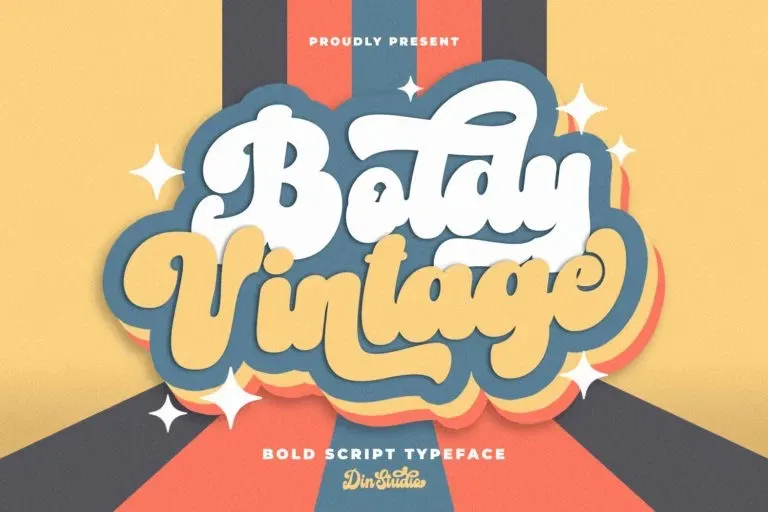
A nova fonte “Boldy Vintage Font”, categorizada como Script Fonts, é uma escolha perfeita para criar design único e inovador. Esta tipografia é marcada por um forte estilo script com um toque vintage que se destaca do restante. Foi criado pelo talentoso designer Din Studio. A fonte traz uma sensação de nostalgia moderna, onde cada traço desenhado a mão e curva exibe originalidade. Ela adicionará uma nota de luz e modernidade para qualquer tipo de layout onde seja aplicada. A “Boldy Vintage Font” é particularmente ótima para maximizar o varejo e alegria de um design, sendo perfeita para criar marcas inovadores, logos, menus e gráficos em mídias sociais. Esta fonte tem uma aparência leve e giratória que permite uma grande diversão criativa. Suas características permitem que você faça desenhos divertidos e imaginativos sem perder a elegância e personalidade necessária para qualquer projeto visual. Ideal tanto para os mais ativos como para aqueles que procuram algo vintage, esta fonte é um ótimo adorno para seu próximo design gráfico.